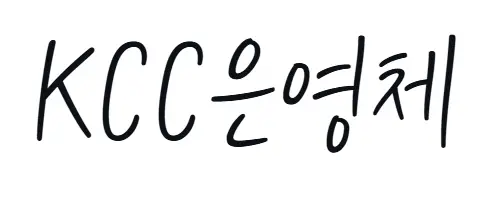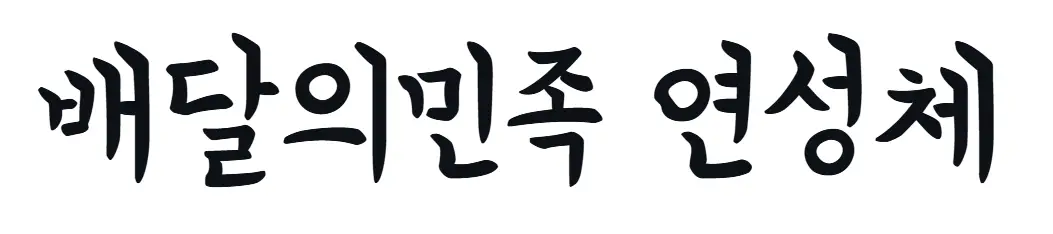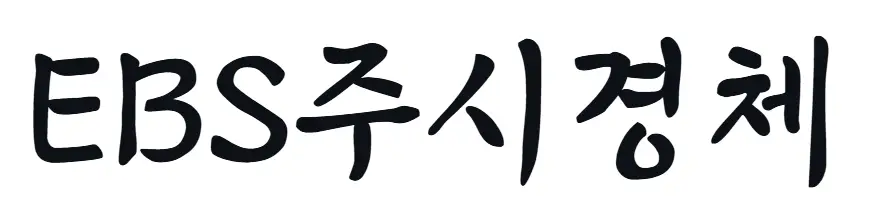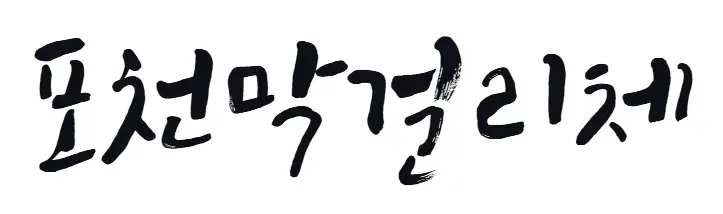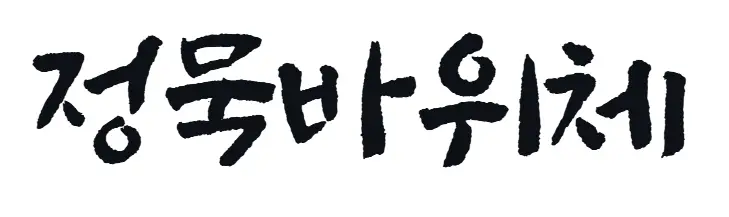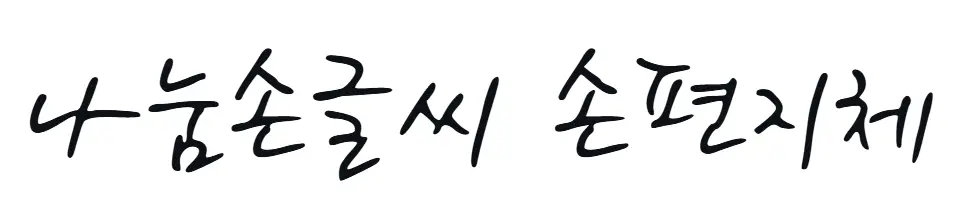
붓글씨 폰트 무료 다운로드 추천 – 상업적 이용
내 디자인에 감성 한 스푼! 무료 붓글씨 폰트로 저작권 걱정 없이 멋진 결과물을 만들어 보세요. 다양한 폰트들을 쉽게 찾아보고 활용하는 방법을 알려드릴게요.
혹시 디자인 작업하다가 '이건 정말 찰떡이다!' 싶은 붓글씨 폰트를 발견했는데, 상업적 이용이 가능한지 몰라서 포기했던 경험 있으신가요? 제가 딱 그랬거든요! 😢
감성적인 붓글씨 서체는 정말 매력적이지만, 저작권 문제 때문에 사용하기가 늘 조심스러웠어요. 그런데 찾아보니 생각보다 무료로 상업적 이용까지 가능한 붓글씨 폰트가 많더라고요! 오늘은 제가 직접 써보고 괜찮다고 느꼈던 붓글씨 폰트들을 소개해 드릴게요. 함께 저작권 걱정 없이 멋진 디자인을 만들어 볼까요? 😊
붓글씨 폰트, 왜 필요할까? 🤔
요즘 콘텐츠들을 보면 붓글씨 폰트가 정말 많이 사용되는 걸 알 수 있어요. 단순히 예뻐서만은 아닌데요, 붓글씨 폰트는 특유의 인간미와 아날로그 감성을 담아내기에 아주 탁월하답니다. 딱딱한 고딕체나 명조체로는 표현하기 어려운 따뜻함, 강렬함, 혹은 유머러스함까지 다양한 분위기를 연출할 수 있죠.
예를 들어, 전통적인 느낌의 제품 포장이나, 손글씨 느낌이 필요한 카페 메뉴판, 아니면 진정성 있는 메시지를 전달하고 싶을 때 붓글씨 폰트만큼 효과적인 게 없어요. 독자가 글자를 통해 감정까지 느낄 수 있게 해준달까요? 저는 개인적으로 여행 블로그 포스팅 할 때 제목에 붓글씨 폰트를 자주 활용하는데, 뭔가 더 정감 가고 좋더라고요! 😊
붓글씨 폰트의 매력은 단순히 시각적인 아름다움을 넘어, 전달하고자 하는 메시지에 감성적 깊이를 더해준다는 점이에요. 덕분에 독자의 몰입도를 높이고, 브랜드의 개성을 효과적으로 표현할 수 있습니다.
상업적 이용 가능한 붓글씨 폰트 추천 📊
자, 이제 가장 중요한! 상업적으로도 마음껏 쓸 수 있는 붓글씨 폰트들을 소개해 드릴게요. 제가 직접 사용해보면서 만족도가 높았던 폰트들이니, 여러분도 분명 마음에 드실 거예요.
아래 표로 정리해두었으니, 특징과 저작권 요약을 한눈에 비교해보세요!
무료 붓글씨 폰트 비교
| 폰트명 | 특징 | 상업적 이용 | 다운로드 링크 |
|---|---|---|---|
| KCC 은영체 | 부드러우면서도 힘 있는 붓글씨 느낌. 전통적인 분위기에 잘 어울려요. | 출처(저작가)만 밝히면 상업적/비영리적 이용 및 저작물 변경 가능. | 공식 다운로드 |
| 배달의민족 연성체 | 제주도 호박엿 가판대 모티브. 울퉁불퉁 리듬감 있는 붓글씨체. | 자유롭게 수정/변경하여 영리적/비영리적 목적 사용 가능. 폰트 파일 자체 유료 판매 금지. | 공식 다운로드 |
| 정선아리랑 뿌리체 | 한국적인 선의 느낌, 춤사위 같은 리듬감이 특징. | 개인 및 기업 사용자 모두 무료 제공, 인쇄물/광고물 등 상업적 사용 가능. 폰트 자체 유료 판매 및 수정/재배포 금지. | 공식 다운로드 |
| EBS 주시경체 | 주시경 선생의 육필본 원본을 기반으로 한글학회와 협력하여 제작. | 학교, 개인, 공공기관 누구나 무료 사용 가능. 영상, 인쇄, 웹, 모바일 등 상업적 이용 가능. 소스코드 수정 및 재배포/재판매 금지. 음란물, 반사회적 제작물 사용 불가. | 공식 다운로드 |
| 포천막걸리체 | 80년 전통 포천 막걸리와 장인정신이 담긴 서체. | 개인 및 기업 사용자에게 무료 제공. 유료 양도/판매 금지. 원본 형태 그대로 사용. 저작권자 밝히고 사용 권장. | 공식 다운로드 |
| 정묵바위체 | 단단하고 우직한 느낌의 캘리그라피 서체. | 개인/기업/상업적 용도 사용 허락. 재판매/파일 수정 금지. | 공식 다운로드 |
| 나눔손글씨 손편지체 | 엄마의 글씨를 모티브로 한 따뜻한 감성 서체. | 기업/단체/개인 누구나 무료 사용 가능. 폰트 파일 유상 제공/판매/배포 금지. | 공식 다운로드 |
붓글씨 폰트 활용 팁 & 저작권 확인 방법 🧮
좋은 폰트를 다운로드받았다면, 이제 어떻게 활용해야 할지 고민될 텐데요. 제가 꿀팁 몇 가지와 함께 저작권 재확인 방법을 알려드릴게요!
📝 붓글씨 폰트 활용 공식
강조 효과 = (개성 있는 붓글씨 폰트) + (적절한 여백) + (심플한 배경)
예시를 통해 좀 더 자세히 설명해 드릴게요:
활용 예시
1) 짧은 문구나 슬로건에 적용하여 시선을 집중시킵니다.
2) 긴 본문보다는 제목, 소제목, 강조하고 싶은 부분에 사용합니다.
→ 붓글씨 폰트의 가독성을 고려하여 메인 텍스트보다는 포인트로 활용하는 것이 중요해요!
디자인 완성도를 높이는 붓글씨 폰트 활용법 👩💼👨💻
단순히 폰트만 잘 고른다고 끝이 아니죠! 붓글씨 폰트를 활용하여 디자인의 완성도를 높이는 몇 가지 팁을 더 드릴게요. 제가 직접 작업하면서 느꼈던 점들이니 분명 도움이 되실 거예요.
강약 조절이 핵심인데요, 모든 텍스트에 붓글씨 폰트를 사용하기보다는 중요한 문구에만 적용해서 시각적인 재미와 강조 효과를 동시에 노리는 거죠. 예를 들어, 메인 배너의 제목은 붓글씨로, 내용은 가독성 좋은 일반 서체로 구성하면 훨씬 세련된 느낌을 줄 수 있어요.
붓글씨 폰트는 그 자체로 강한 인상을 주기 때문에, 다른 디자인 요소들과의 조화가 중요해요. 배경 이미지나 색상, 그리고 다른 서체들과의 균형을 잘 맞춰야 최상의 결과물을 얻을 수 있습니다.
실전 예시: 붓글씨 폰트로 로고 만들기 📚
제가 실제로 붓글씨 폰트를 활용해서 간단한 개인 블로그 로고를 만들었던 경험을 예시로 보여드릴게요. 막상 해보면 정말 쉽고, 결과물도 너무 만족스러워서 깜짝 놀라실 거예요.
사례: 'OOO의 작업실' 로고 제작
- 사용 폰트: 배달의민족 연성체 (울퉁불퉁한 개성 강조)
- 목표: 친근하면서도 전문가적인 느낌의 블로그 로고 제작
제작 과정
1) 'OOO의 작업실' 문구를 연성체로 작성 후, 글자 간격을 조절하여 가독성 확보.
2) 배경색은 따뜻한 아이보리 계열로, 글자색은 차분한 다크 그레이로 설정하여 폰트가 돋보이게 함.
최종 결과
- 개성 있고 기억하기 쉬운 로고 완성: 방문자들이 로고만 봐도 친근한 느낌을 받게 되었어요.
- 브랜드 아이덴티티 강화: 블로그의 아날로그 감성과 수작업 이미지가 잘 연결되었습니다.
보셨죠? 간단한 과정만으로도 이렇게 멋진 결과물을 만들 수 있답니다. 여러분도 오늘 소개해드린 폰트들을 활용해서 나만의 멋진 디자인을 시도해보시면 좋겠어요!
마무리: 핵심 내용 요약 📝
오늘은 상업적 이용이 가능한 붓글씨 폰트들을 알아보고, 저작권 관련 주의사항과 활용 팁까지 함께 이야기 나눠봤는데요. 어떠셨나요? 붓글씨 폰트는 우리 디자인에 정말 특별한 감성을 불어넣어 줄 수 있는 멋진 도구라고 생각해요!
붓글씨 폰트 활용 핵심 요약!